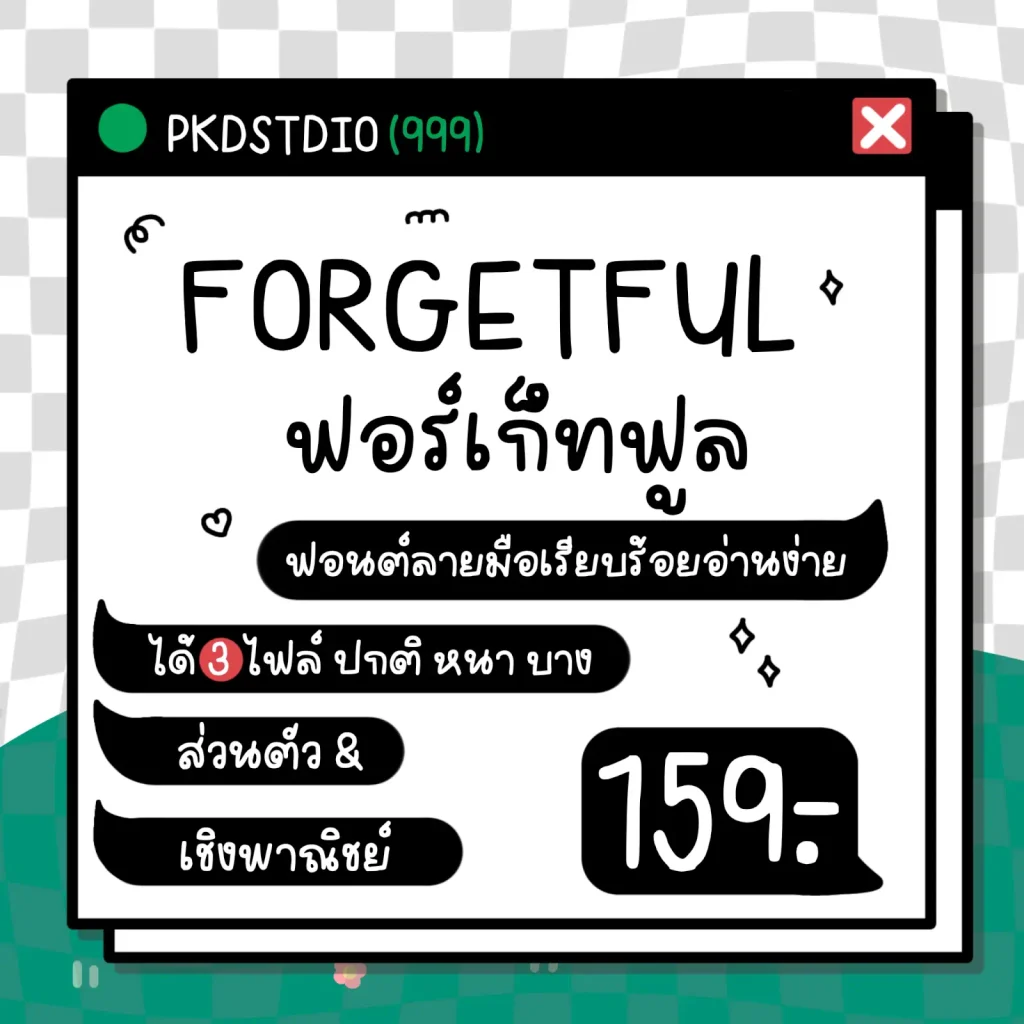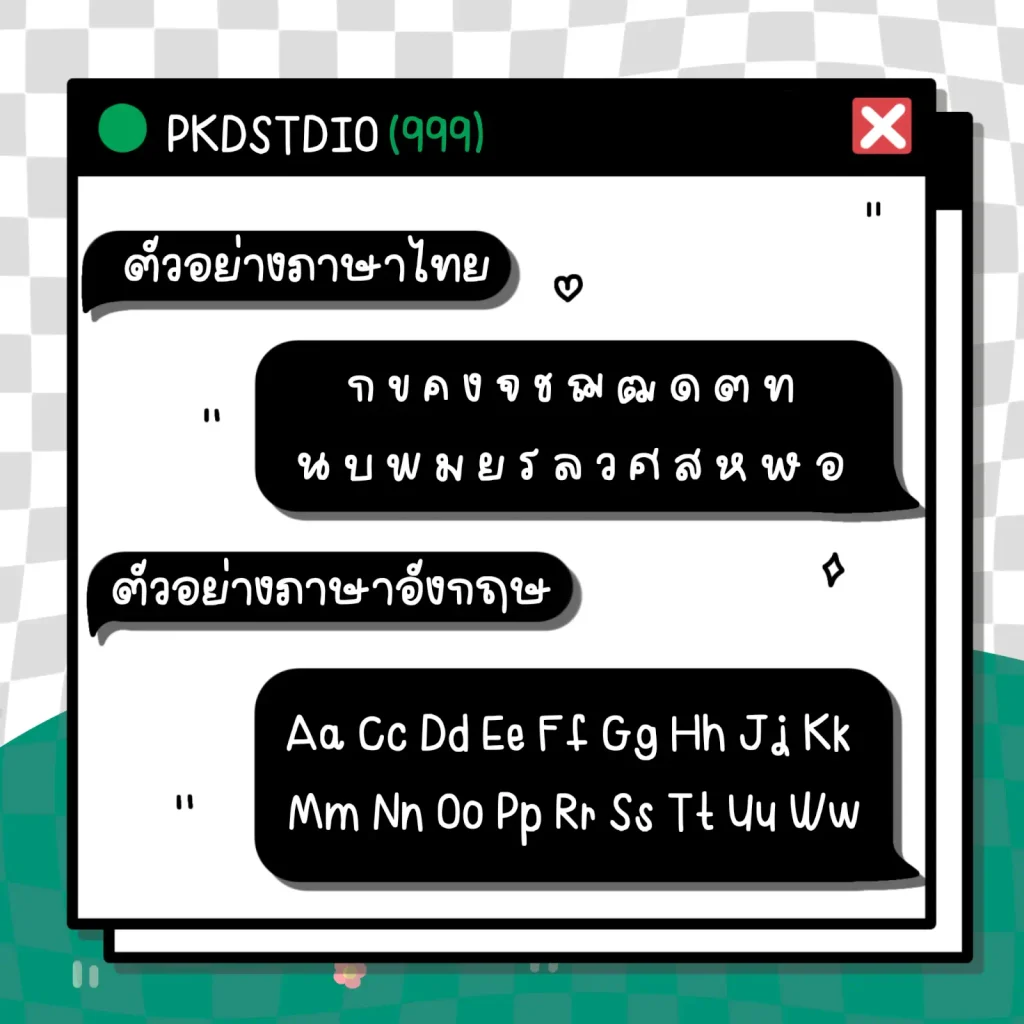
ฟอร์เก็ทฟูลฟอนต์ (PKD FORGETFUL) – ฟอนต์ลายมือน่ารัก สดใส เป็นกันเอง เหมาะสำหรับงานคอนเทนต์ โพสต์โซเชียล สติกเกอร์ คาเฟ่ และงานออกแบบทั่วไป
- มีตัวอักษรโปร่งผสมในบางตำแหน่ง
- ไม่มีตัวอักษรโปร่งผสม
- รองรับภาษาไทย ภาษาอังกฤษ ตัวเลข และสัญลักษณ์
ฟอร์เก็ทฟูลฟอนต์ (PKD FORGETFUL)